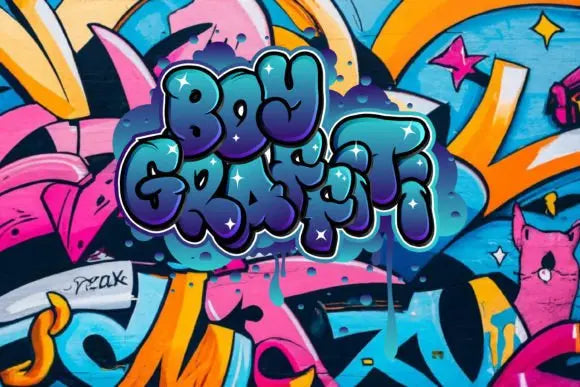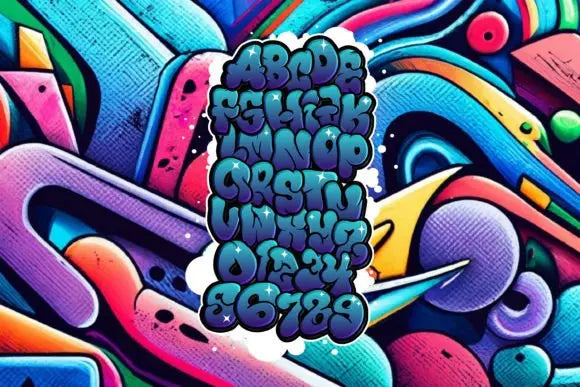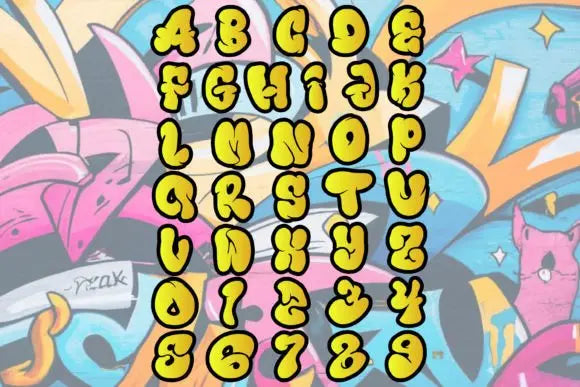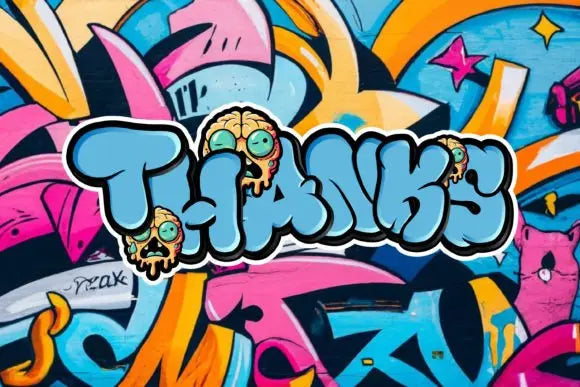
Fuente de graffiti de niño
Boy Graffiti Font: descubre el mundo vanguardista y urbano de las fuentes de graffiti.
Desde letras en negrita hasta diseños complejos, explora una colección de fuentes de graffiti para tu próximo proyecto creativo.
¿Buscas una fuente de graffiti genial para usar? Echa un vistazo a nuestra colección de las mejores fuentes de graffiti que añaden estilo urbano y nerviosismo a tus diseños. Ya sea que estés trabajando en un proyecto de arte callejero o quieras darle a tus diseños gráficos un aspecto inspirado en el graffiti, estas fuentes harán una declaración audaz.